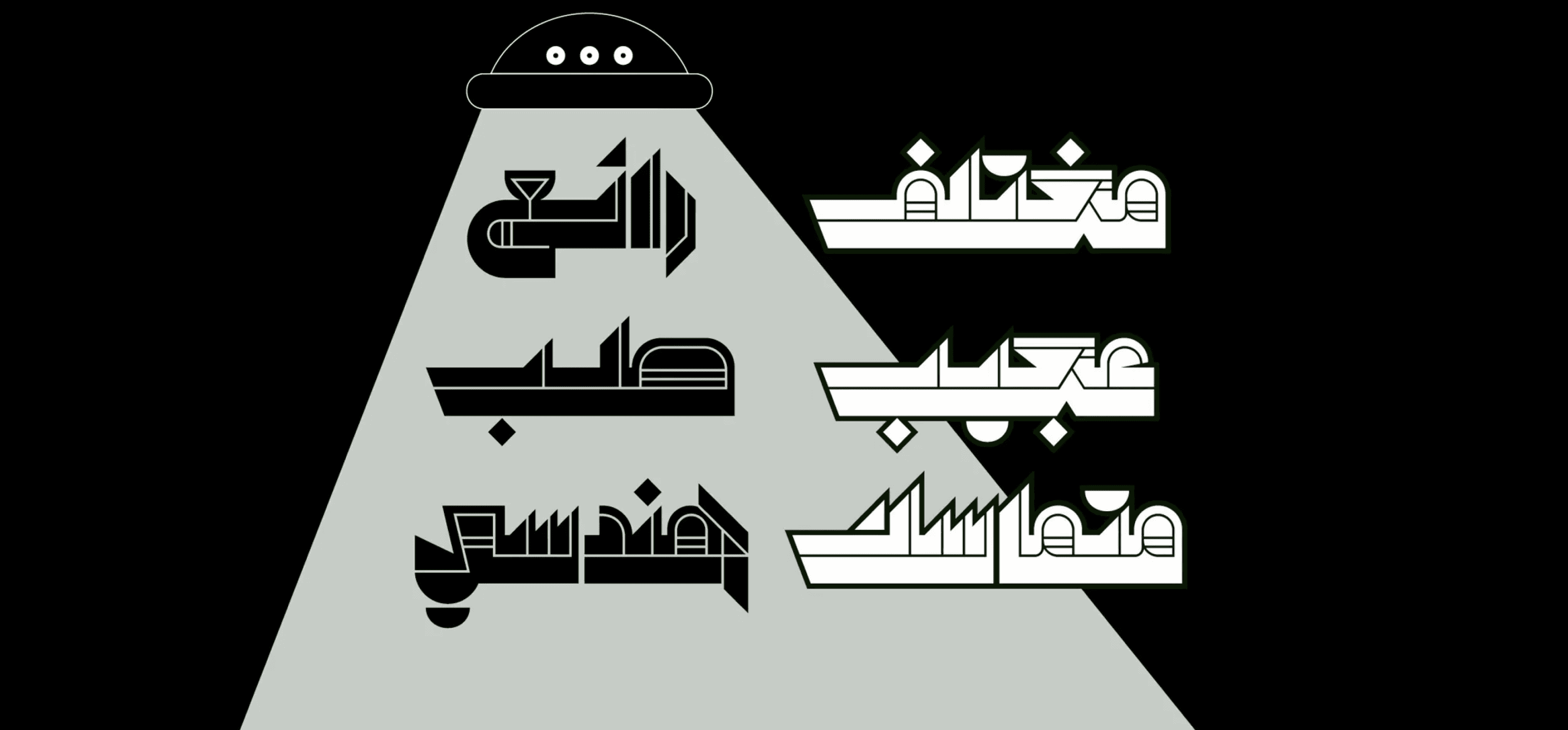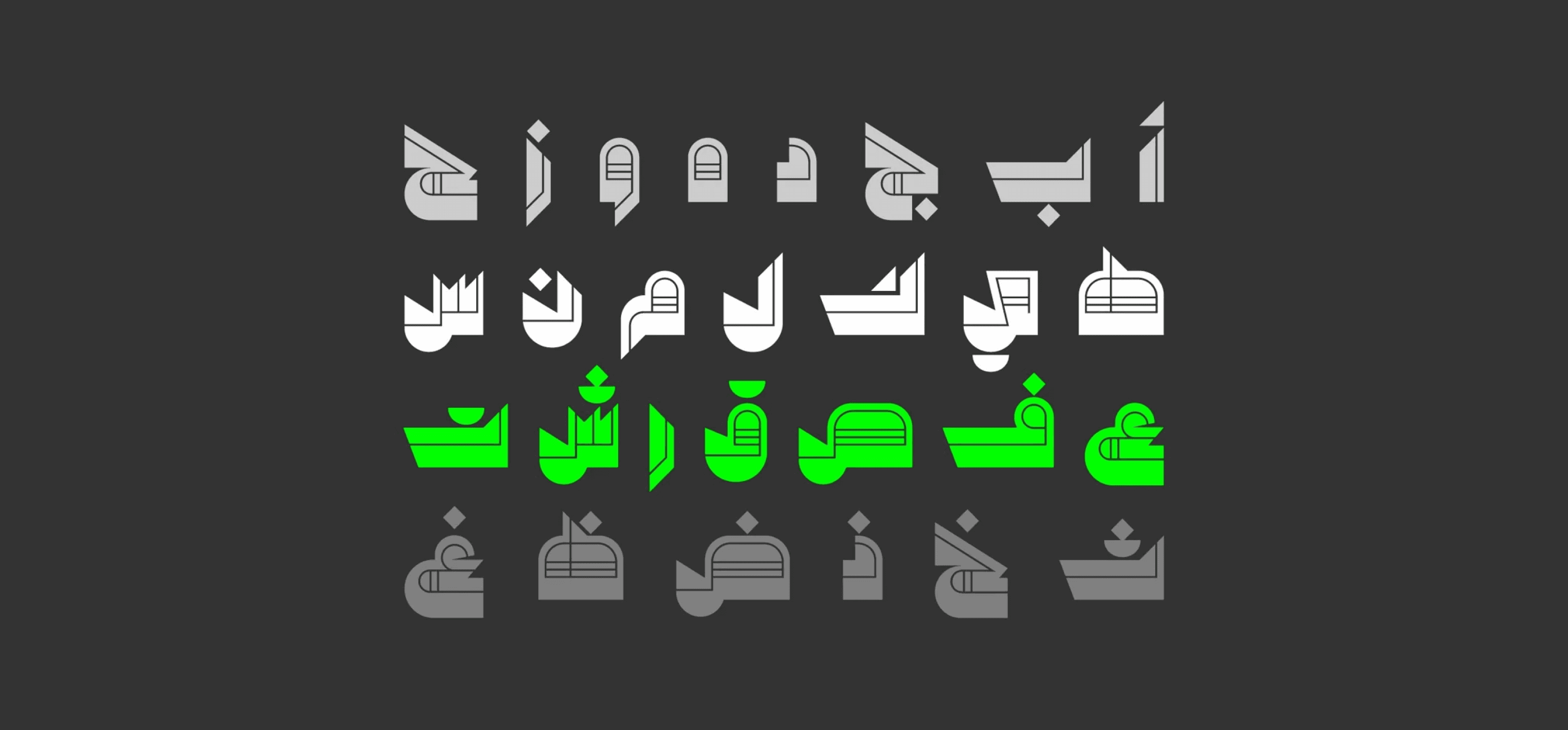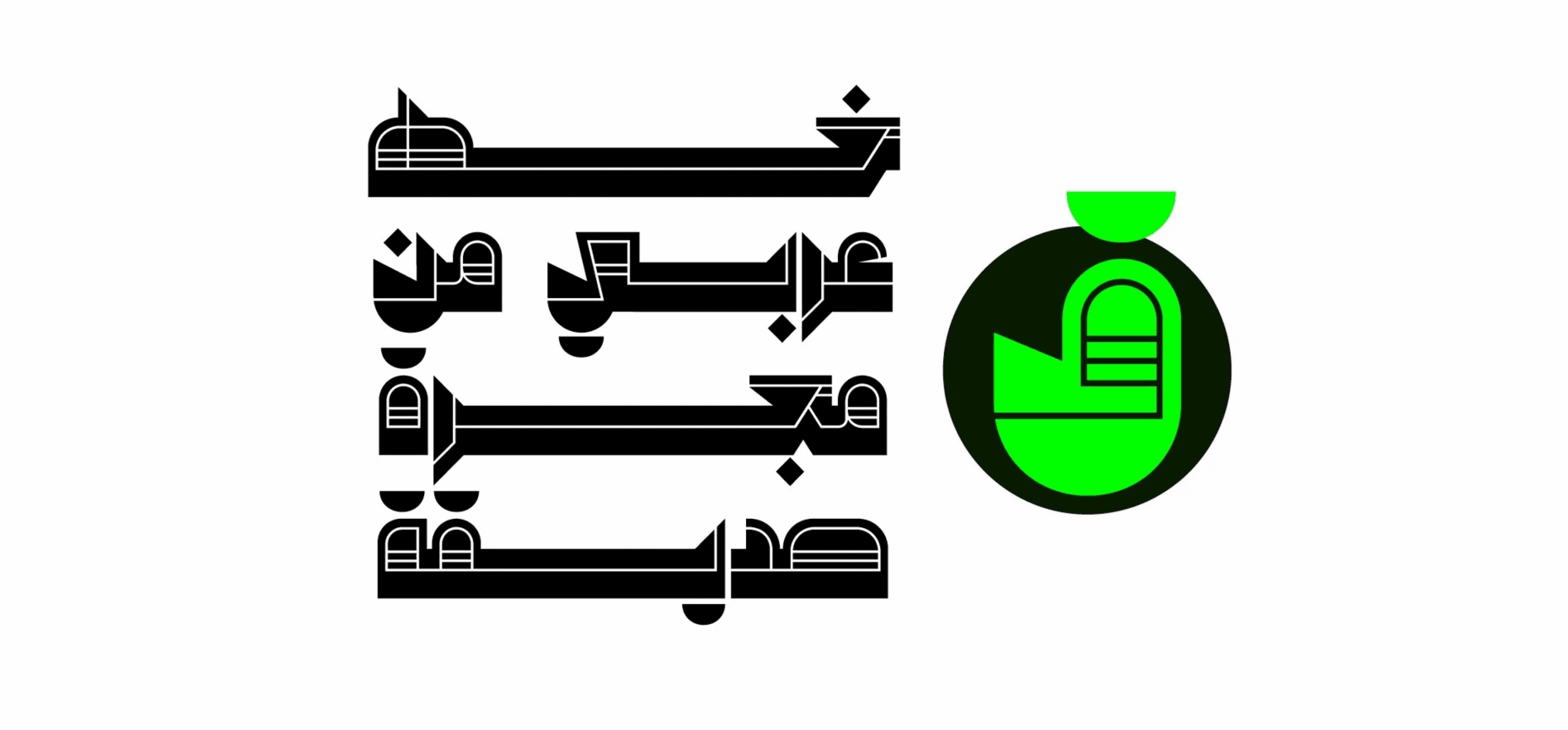
خط عربي بتصميم هندسي مستقبلي مستوحى من ثقافة الخيال العلمي والفضاء، يأتي بأسلوب بصري فريد يمزج بين الجرأة والابتكار.
يعتمد الخط على أسلوب الـ Blackletter لكن برؤية عربية حديثة، ما يمنحه طابعًا حادًا وزاويًا مثاليًا للعناوين، الملصقات، والتصاميم الجريئة.
فضائي هو خيار مثالي لأي مشروع يسعى للتميز والاختلاف بطابع فني معاصر وغير تقليدي.